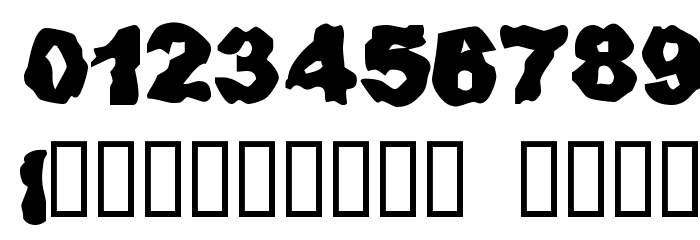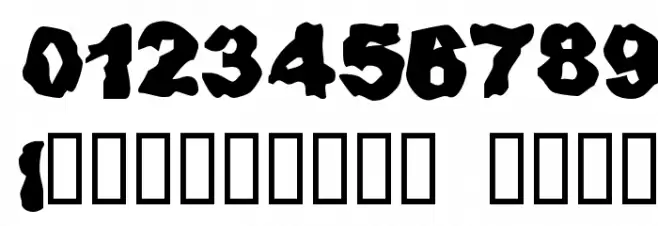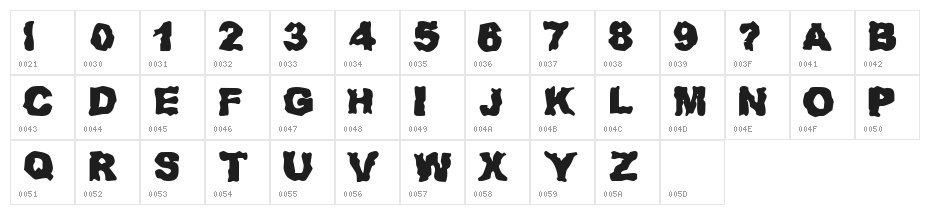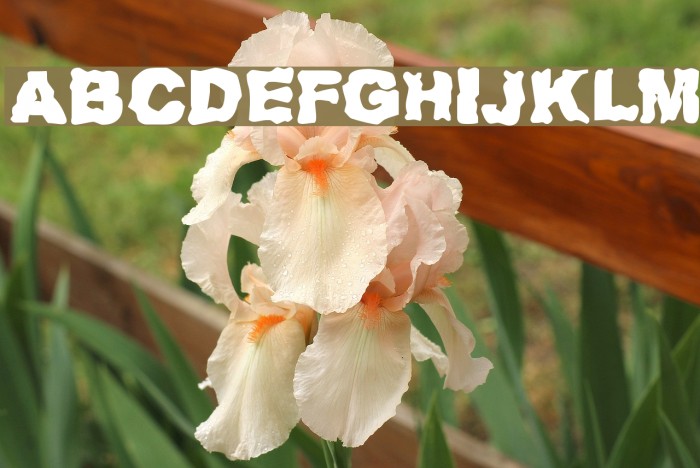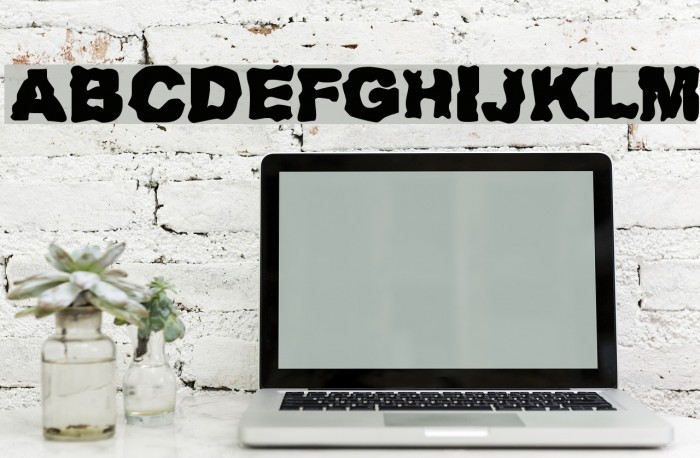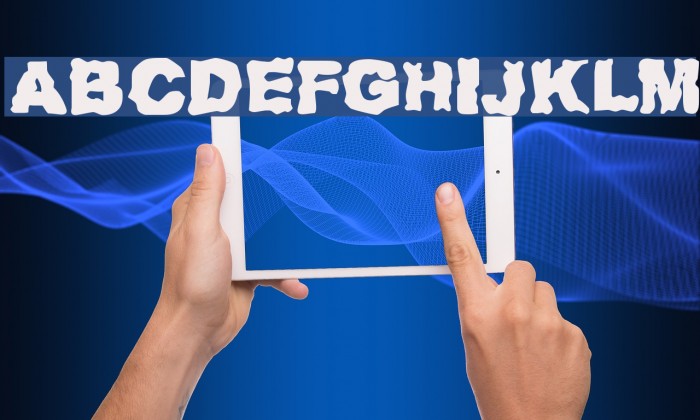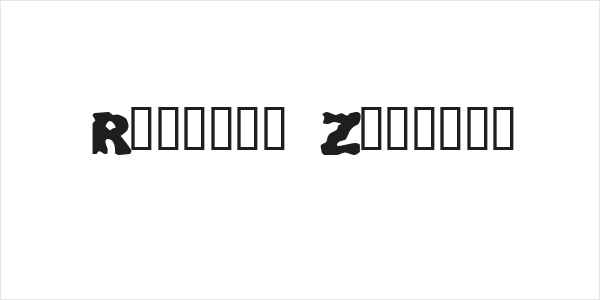
Redneck Zombies Font
| Projetos propostos | Perfect for horror movie posters, Halloween event flyers, edgy apparel designs, or any project needing a bold, attention-grabbing font. |